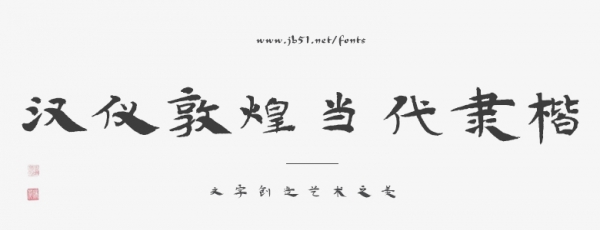
汉仪敦煌当代隶楷秉持“修旧如旧”的设计理念,在保留底本笔触与书写逸趣的基础上,适当提升一致性,着重呈现汉字由隶书向楷书演变时期古朴自然的书写风貌。既还原了敦煌写经的原生气质,也满足现代用字需求。
汉仪敦煌当代隶楷整体风格灵活随性,充分还原敦煌写经的民间书写意趣,在规范用字与古籍原貌间取得平衡,使千年写经艺术在当代得以传承。该字体广泛适用于魏晋南北朝专题出版物、敦煌文献与佛学典籍印制、敦煌及魏晋历史展馆展陈、魏晋国风品类品牌、河西地域文旅伴手礼包装等多元场景,以兼具骨力与温度的笔墨气韵传递东方书法之美,满足传统文化与当代设计融合的多元审美诉求。